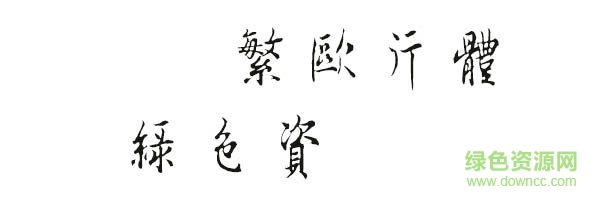
迷你繁歐行字體是一款迷你繁歐體繁體字,官方打造而成,采用繁體傳統(tǒng)字形打造,主要用于廣告創(chuàng)意等方面,喜歡就來綠色資源網(wǎng)下載體驗(yàn)唄!
迷你繁歐行是一款非常特別的簡(jiǎn)體中文漢字,主要應(yīng)用于創(chuàng)意設(shè)計(jì)方面,字庫可能不完整,但也可以適用于名片設(shè)計(jì)、平面設(shè)計(jì)、廣告設(shè)計(jì)、報(bào)紙雜志、企業(yè)LOGO、商標(biāo)注冊(cè)、電視臺(tái)廣告等領(lǐng)域,有喜歡的網(wǎng)友可免費(fèi)下載收藏。